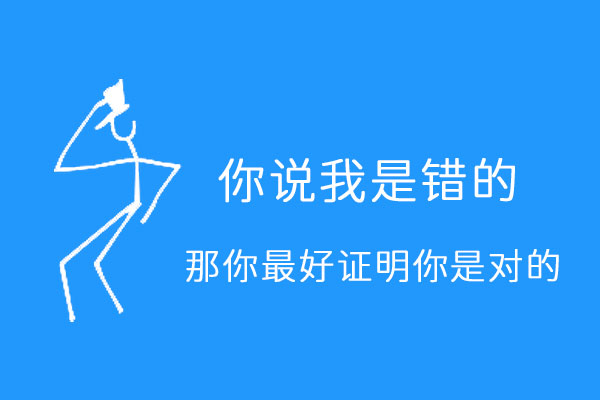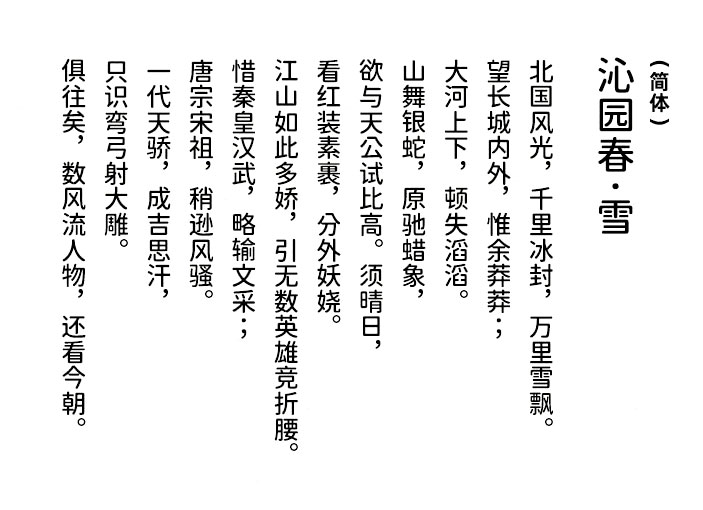
江城圆体
在寻找一款适合的圆润中文字体时,我们经常会面临没有合适选择的困境。过去,大部分设计师会选择使用“思源柔黑体”或者源泉圆体,然而这两款字体都有其局限性。源泉圆体是台湾设计师改造的,因此它的字形更偏向于台湾的使用习惯。
幸运的是,国内有一位兼具设计和编程才华的大神级人物刘鹏,根据源泉圆体进行改造,把一些台湾习惯的字形进行了简体化修正。他发布了一款更适合大陆设计师使用的字体——“江城圆体”。这款字体在保持源泉圆体的基础上,简化了字符并增加了六个字重,十分贴心。
江城圆体效果预览
江城圆体字体效果预览